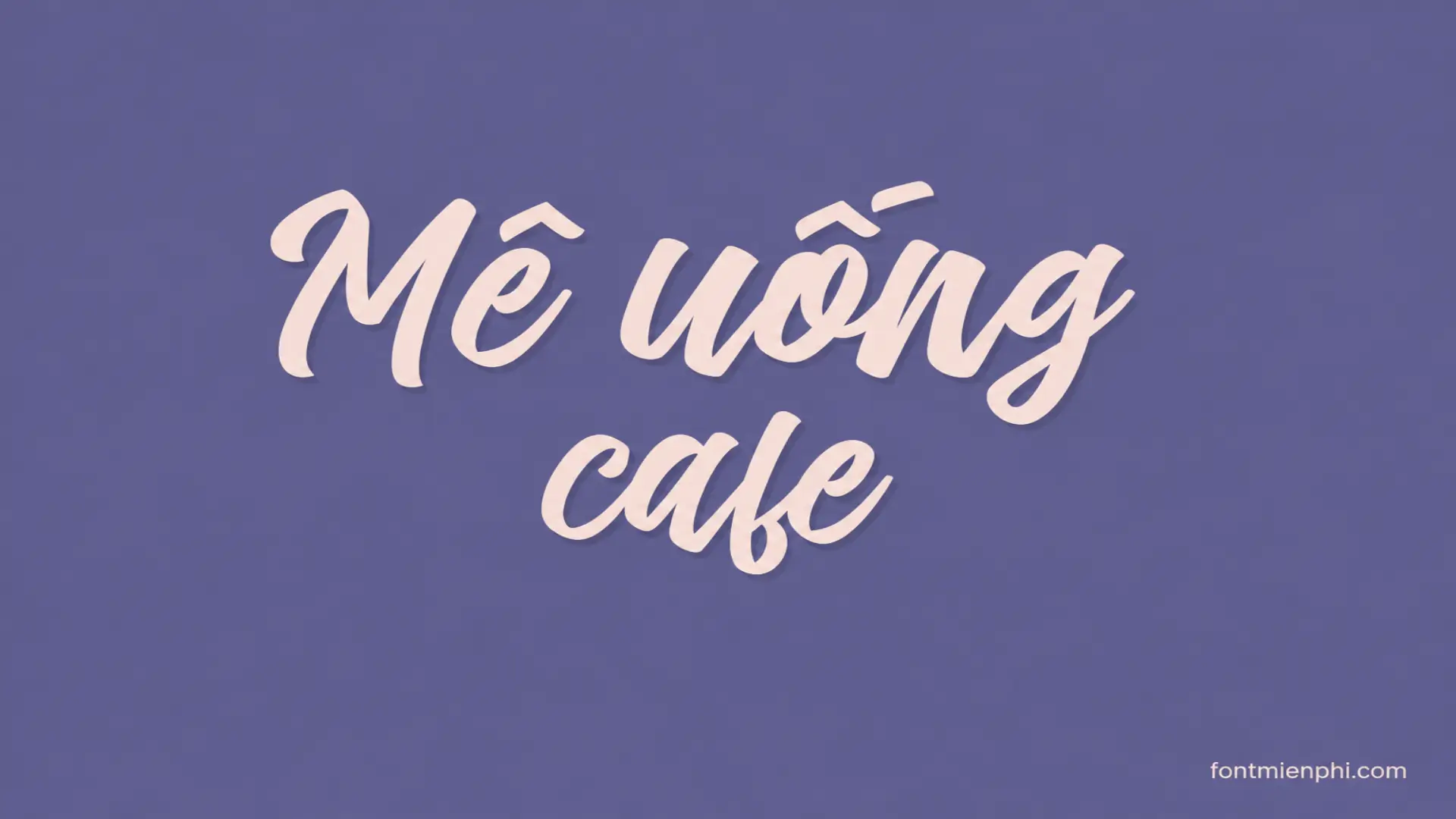
Font Việt hóa 1FTV VIP Broline Script
Tải Font Việt Hóa 1FTV VIP Broline Script – Phông Chữ Viết Tay Thanh Lịch, Bay Bổng
Chào mừng bạn đến với Fontmienphi.com! Nếu bạn đang tìm kiếm một phông chữ mang đậm chất nghệ thuật, mềm mại và uyển chuyển như những nét bút viết tay thực sự, thì Font Việt hóa 1FTV VIP Broline Script chính là sự lựa chọn hoàn hảo. Đây là một trong những bộ font Script (chữ thảo/chữ viết tay) được giới thiết kế săn đón nồng nhiệt nhất cho các dự án cần sự sang trọng và lãng mạn.
1. Giới thiệu về Font Việt Hóa 1FTV VIP Broline Script
1FTV VIP Broline Script là một phông chữ nghệ thuật được thiết kế với những đường nét nối liền mạch (continuous strokes), mô phỏng lại nét chữ ký và nghệ thuật Calligraphy hiện đại. Sự kết hợp giữa các nét thanh, nét đậm nhịp nhàng giúp phông chữ này toát lên một vẻ đẹp vô cùng tự nhiên, phóng khoáng nhưng không kém phần thanh lịch.
Điểm đắt giá nhất của phiên bản này chính là quá trình Việt hóa chuẩn VIP từ 1FTV. Các dấu câu tiếng Việt (hỏi, ngã, nặng, sắc, huyền) được tinh chỉnh cực kỳ tỉ mỉ, đặt đúng trọng tâm và uốn lượn hài hòa với nét chữ gốc. Nhờ đó, các Designer có thể thoải mái gõ những đoạn văn bản tiếng Việt dài mà các ký tự vẫn nối với nhau mượt mà, không hề bị gãy nét hay lỗi font.
2. Đặc điểm nổi bật của Font Broline Script
• Nét chữ bay bổng, lãng mạn: Mang lại cảm giác mềm mại, cá nhân hóa và giàu cảm xúc cho mọi ấn phẩm thiết kế.
• Ligatures (Ký tự nối) phong phú: Hỗ trợ các ký tự nối đặc biệt giúp cụm từ trông tự nhiên như được viết ra từ một nghệ nhân thư pháp.
• Chất lượng hiển thị xuất sắc: Từng đường vector được trau chuốt sắc nét, hiển thị hoàn hảo trên cả ấn phẩm in ấn lẫn nền tảng kỹ thuật số.
3. Ứng dụng tuyệt vời của Broline Script trong thiết kế
Với sắc thái tinh tế và sang trọng, Font Việt hóa 1FTV VIP Broline Script là “nàng thơ” cho hàng loạt các dự án thiết kế đặc thù:
💌 Thiết kế Thiệp cưới & Sự kiện (Wedding Invitation)
Không có gì phù hợp để viết tên cô dâu, chú rể hay những lời chúc lãng mạn trên thiệp cưới hơn là một font Script bay bổng. Broline Script sẽ mang đến sự sang trọng, tinh tế và đầy tính trân trọng cho các ấn phẩm cưới hỏi.
✍️ Thiết kế Chữ ký & Watermark Nhiếp ảnh
Nếu bạn là một nhiếp ảnh gia (Photographer) hoặc nhà sáng tạo nội dung cần một font chữ để làm Watermark đóng dấu bản quyền lên hình ảnh, Broline Script sẽ tạo ra một “chữ ký” cực kỳ nghệ thuật và chuyên nghiệp.
🌿 Nhận diện thương hiệu (Mỹ phẩm, Spa, Hoa tươi)
Sự mềm mại của phông chữ này rất lý tưởng để làm Logo hoặc bao bì sản phẩm cho các thương hiệu hướng tới phái đẹp như: tiệm nail, spa làm đẹp, thương hiệu thời trang nữ, hoặc các cửa hàng hoa tươi cao cấp.